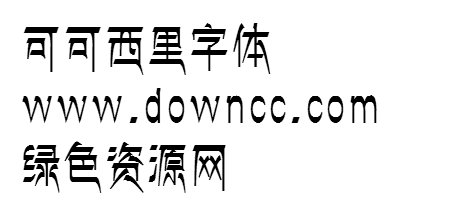
可可西里字體是在可可西里影視中較常見到的一款藏文字體,中英文都有著不錯(cuò)的藝術(shù)風(fēng)格,造型精簡而獨(dú)具地域風(fēng)情,快來綠色資源網(wǎng)試試吧!
電影《可可西里》海報(bào)“可可西里”四個(gè)字根據(jù)藏文設(shè)計(jì)的。要知道海報(bào)設(shè)計(jì)以及其它正規(guī)的設(shè)計(jì)是不允許出現(xiàn)字庫里的字體的設(shè)計(jì)師需要自己設(shè)計(jì)出來專屬的字體原創(chuàng)性一致。
可可西里字體采用方正藏意字體設(shè)計(jì)而成,暫推薦該字體下載!